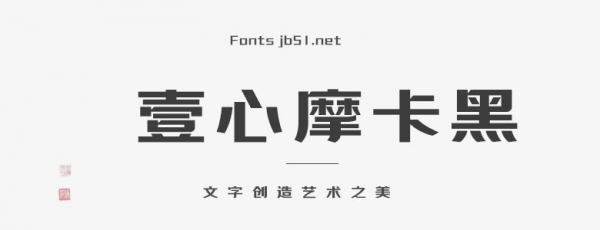
壹心摩卡黑是一款創(chuàng)意的時(shí)尚黑色字體,適合應(yīng)用于藝術(shù)設(shè)計(jì)、平面宣傳設(shè)計(jì)、網(wǎng)頁(yè)設(shè)計(jì)、書(shū)法字體,海報(bào)設(shè)計(jì)等領(lǐng)域,歡迎喜歡這款字體的朋友下載收藏。